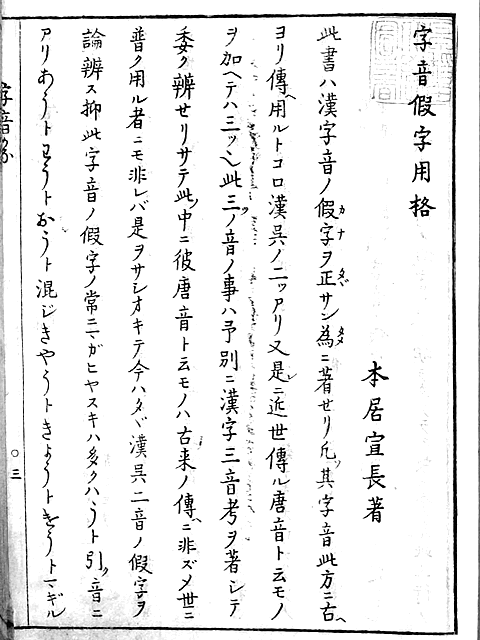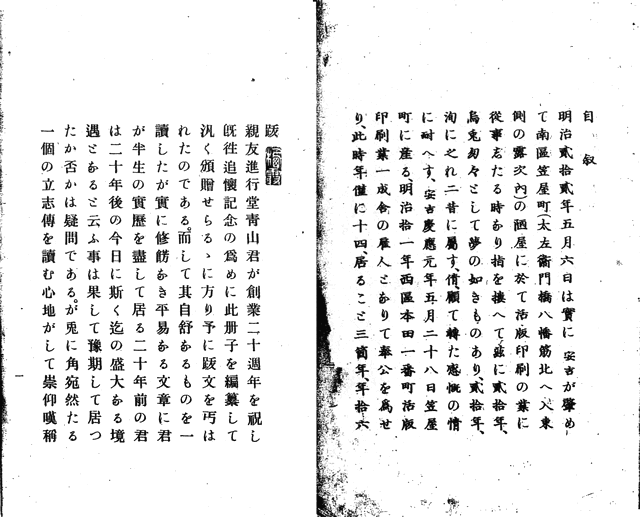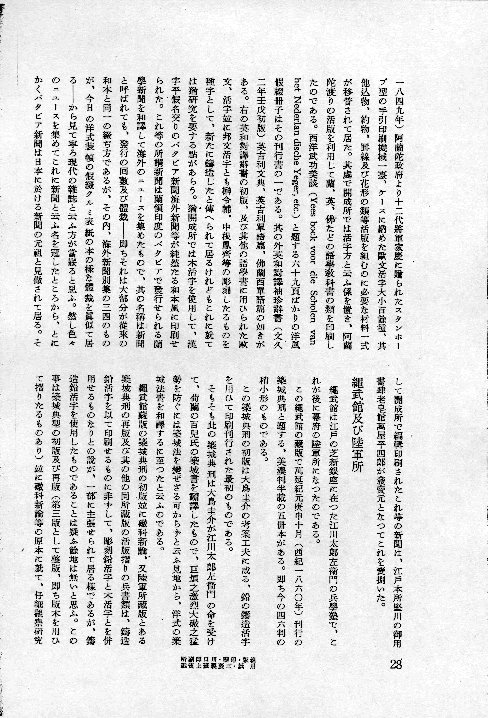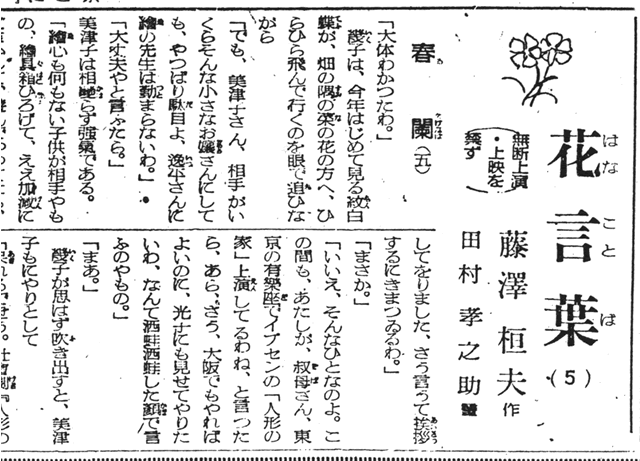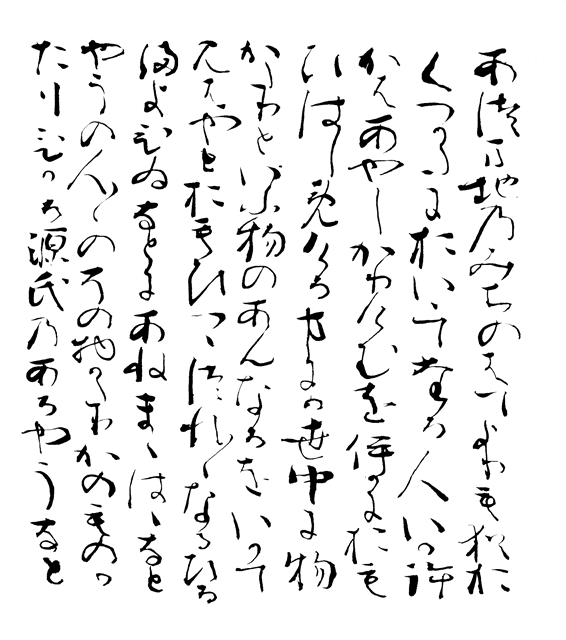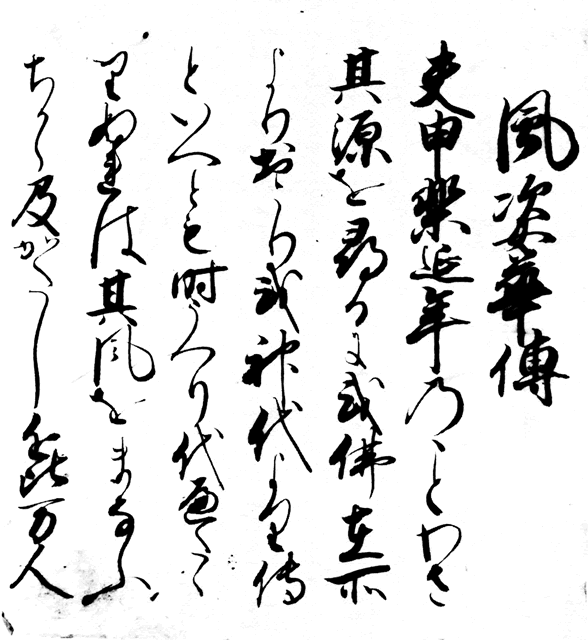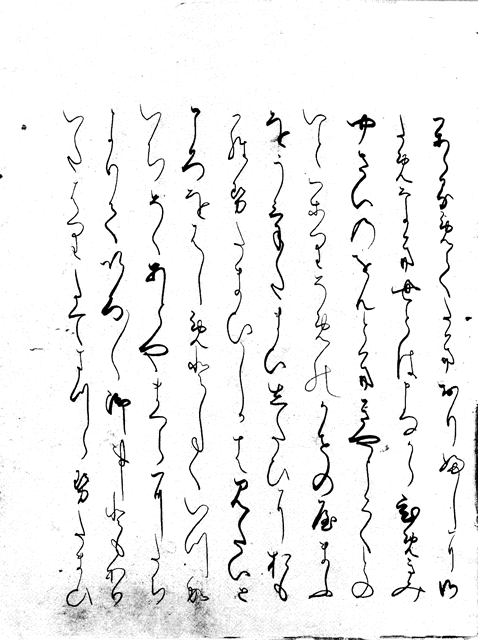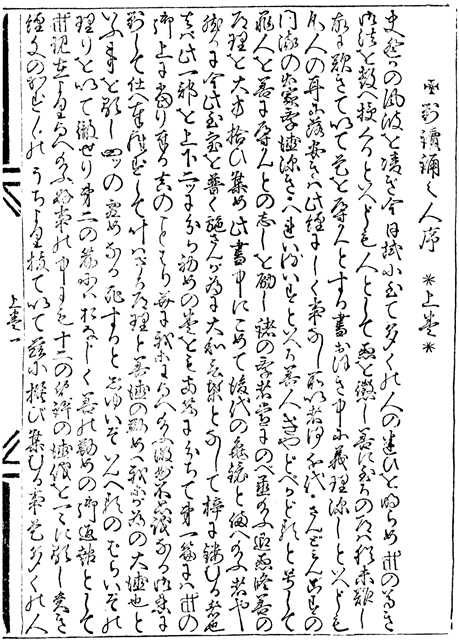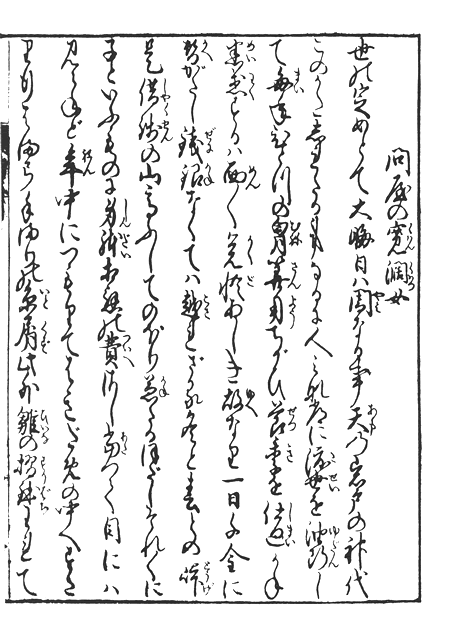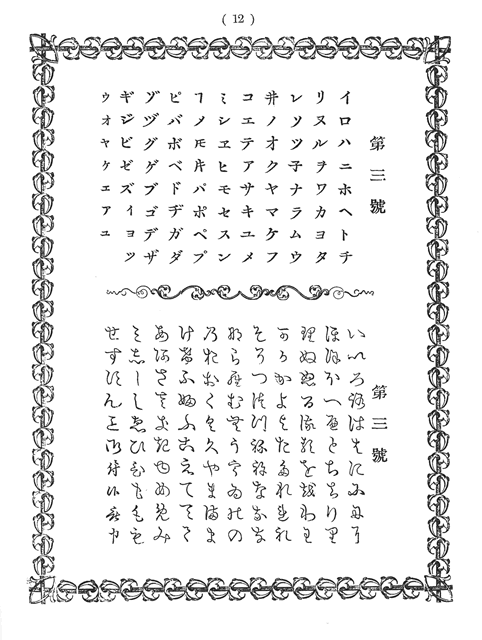
書体の基礎知識 和字書体編
黎明本様体──和字のヴェネチアン・ローマン体
和字(平仮名と片仮名)書体の歴史とは、おもに文芸書をしるした「和様漢字+平仮名」の系統と、おもに学術書をしるした「楷書漢字+片仮名」の系統があります。
前者は欧字書体のイタリック体もしくはスクリプト体に相当し、後者はローマン体に相当するものと考えられます。この「楷書漢字+片仮名」の系統において、片仮名とならんで平仮名が登場したとき、和字のローマン体が誕生したといえるでしょう。
それは江戸時代後期のことです。今回は、国学・蘭学の三冊の書物から、和字のヴェネチアン・ローマン体誕生のそのときにせまっていきたいと思います。
1 『字音假字用格(じおんかなづかい)』 1776 錢屋利兵衞
京都の錢屋利兵衞によって1776年(安永5)に刊行されました。序題は「字音迦那豆訶比」、版心書名は「字音かな」となっています。序は須賀直見が書いています。一冊のみで、27cmサイズの四つ目綴じ製本です。
著者の 本居宣長(1730―1801)は江戸中期の国学者です。伊勢の人で、号を舜庵(春庵)・鈴屋といいます。京都に出て医学を修める一方で、源氏物語などを研究しました。のちに賀茂真淵に入門しました。古道研究をこころざし、「古事記伝」の著述に30余年にわたって専心しました。
また、「てにをは」や用言の活用などの語学説、「もののあはれ」を中心とする文学論、上代の生活・精神を理想とする古道説など、多方面にわたって研究・著述に努めました。
著書に『初山踏(ういやまぶみ)』『石上私淑言(いそのかみささめごと)』『詞の玉緒』『源氏物語玉の小櫛(おぐし)』『古今集遠鏡』『玉勝間』『鈴屋集』などがあります。
2 『仮字本末』 1850  三書堂
国学とは江戸中期に興った文献学的方法による古事記・日本書紀・万葉集などの古典研究の学問で、儒教・仏教渡来以前の日本固有の文化を究明しようとしたものです。契沖(けいちゆう)を先駆とし、荷田春満(かだのあずままろ)・賀茂真淵・本居宣長・平田篤胤(ひらたあつたね)らによって確立しました。皇学(皇国の学の意)ともいいます。
文政年間に書かれた国学者・伴信友(1773―1846)の遺稿をその子信近が校訂し、1850年(嘉永3)3月に長沢伴雄(1806―59)の序を添えたうえで、江戸・大坂・京都の書肆から刊行されたのが『仮字本末』です。
刊本は上巻之上、上巻之下、下巻、付録の合計4冊からなっており、朝鮮綴で薄紺色無地の表紙がつけられています。「楷書漢字+平仮名」が登場した初期の印刷物だと思われます。
3 『歩兵制律』 1865  陸軍所
洋学とは西洋の学問のことです。とくに蘭学とは江戸中期以降、オランダ語によって西洋の学術・文化を研究した学問です。享保年間(1716―1736)、青木昆陽・野呂元丈(のろげんじよう)の蘭書の訳読に始まり、前野良沢(まえのりようたく)・杉田玄白・大槻玄沢(おおつきげんたく)ら多数の蘭学者が輩出、医学・天文学・暦学・兵学・物理学・化学など自然科学全般にわたりました。
大鳥圭介(1833―1911)は、縄武館につとめていたとき、『築城典刑』『砲科新論』を翻訳して、独自の活字をもちいて出版することに着手しました。大鳥は西洋の活字が便利だということを知って、独力で蘭書にもとづいていろいろ研究したそうです。
『歩兵制律』(陸軍所 1865 印刷博物館所蔵)は、オランダの書物を開成所の教員であった川本清一が翻訳し、大鳥の金属活字をもちいて印刷したものです。『歩兵制律』は「楷書漢字+平仮名」で組まれています。
●字音假字用格(じおんかなづかい)
●仮字本末
●歩兵制律
明治本様体──和字のオールド・ローマン体(前編)
長崎製鉄所主任だった本木昌造は、ウィリアム・ガンブルを活版伝習所の技師長として招聘しました。ここでは活字鋳造法と活字版印刷術全般にわたる技術を伝授しました。これがわが国の活字版印刷術の基礎となったのです。
まもなく長崎製鉄所付属活版伝習所は解散し、その源流は二派に分かれました。ひとつは本木昌造の流れを汲む門人達によって全国に覇をとなえた一派で、その代表が東京築地活版鋳造所です。他のひとつは製鉄所にとどまって活字製作に従事した人達で、のちに工部省勧工寮活版所となり、幾多の変遷をへて官業活版の源流を受け継いだのが内閣印刷局(現在の国立印刷局)です。これらとは別に神崎正誼による活版製造所弘道軒では、独自の活字書体をあらたに制作しました。
これらの和字書体に共通するのは、黎明期本様体(和字のヴェネチアン・ローマン体)がもっていた彫刻風の荒々しさが少なくなり、丸みを帯びた動きのなる書風にと変化しているということです。これを明治本様体(和字のオールド・ローマン体)としたいと思います。
1 『二人比丘尼色懺悔』 1889  活版製造所弘道軒
神崎正誼(1837―91)は1874年(明治7)に「活版製造所弘道軒」を創立しました。そして新しい活字書体の版下の揮毫を、書家の小室樵山(正春 1842―93)に依頼しました。
尾崎紅葉の『二人比丘尼色懺悔』(吉岡書籍店 1889)にも、本文に四号相当の弘道軒清朝体が用いられています。新著百種の第一作として刊行されたもので、印刷は国文社です。『二人比丘尼色懺悔』は、奇遇の巻・戦場の巻・怨言の巻・自害の巻からなっています。
2 『長崎地名考』 1893  東京築地活版製造所
株式会社東京築地活版製造所の初代社長・平野富二は、1889年(明治22)に社長を辞任しました。本木昌造の長男・本木小太郎が社長心得になりますが、本木小太郎は病弱だったので、曲田成が3代目社長に就任しています。
香月薫平著『長崎地名考』は、上巻・下巻・附録の3冊からなっています。1893年(明治26)11月に長崎の虎與號商店から発行されています。奥付には、印刷所は東京築地活版製造所、印刷人は曲田成(1846―94)とあります。
3 『内閣印刷局七十年史』 1943  内閣印刷局
印書局は明治5年9月に創設されて、はじめは太政官正院の中におかれていました。明治7年に工部省製作寮所管の活版所(勧工寮が明治6年11月に廃止されて製作寮の所管に移る)を移管併合して、明治8年に大蔵省紙幣寮に属することになります。
1877年(明治10)年4月、大蔵省紙幣局となったときに、紙幣局活版部で『活版見本』が発行されています。ここにみられる平仮名、とりわけ5号平仮名が『内閣印刷局七十年史』の本文で用いられた書体の源流だと思われます。
『内閣印刷局七十年史』の本文に用いられた和字書体は、印刷局の伝統的な書風であり、明治前期の典型的な書風といってもいいのではないでしょうか。
●二人比丘尼色懺悔
●長崎地名考
●内閣印刷局七十年史
明治本様体──和字のオールド・ローマン体(後編)
東京築地活版製造所と並び称せられるのが秀英舎鋳造部製文堂です。1882年(明治 15)東京築地活版製造所から小倉吉蔵を招いて製文堂を創設して、活字の製造販売に進出したのがはじまりです。秀英舎は、1935(昭和10)に日清印刷と合併して大日本印刷となりました。
青山進行堂活版製造所は東京築地活版製造所系統の活字書体を継承していたと思われます。江川活版製造所と特約して活字製造に着手し、都村活版製造所、岡島活版所の活字書体を継承しましたが、1916年(大正5)には「篆書ゴシック」を開発して業界の注目を集めました。国光社は吉田晩稼が版下を書いたといわれる独自の活字書体を開発しています。
これらの和字書体もまた、丸みを帯びた動きのある明治本様体(和字のオールド・ローマン体)ですが、昭和本様体(和字のトランジショナル・ローマン体)の萌芽もみられます。
1 『尋常小學國語讀本 修正四版』 1901  国光社
西澤之助(1848―1929)は1888年(明治21)に国光社を創立しました。国光社は伝統的な女子教育の雑誌 『女鑑』 などで一定の地歩を占めました。
1900年(明治33)に西澤之助は国光社社長を辞し、日本女学校を設立しています。また国光社は多くの教科書を発行している大手教科書会社でもありました。
国光社活字とは国光社が独自に開発したとされる書体で、吉田晩稼(香竹1830―1907)が版下を書いたといわれています。
2 『少年工芸文庫第八編 活版の部』 1902  秀英舎
『少年工芸文庫』は全12冊発行されています。著者の石井研堂(民司1865―1943)は、民衆の立場から明治以来の日本の近代化を探求・記録した博物学者です。
発売元の博文館は、明治時代には日本の出版界をリードしていましたが、大正から昭和にかけて雑誌を中心に発展してきた講談社などに押され、終戦後に解散してしまいました。大日本印刷の前身の秀英舎で印刷されていますので、本文はいわゆる秀英舎前期四号です。
3 『富多無可思』 1909  青山進行堂活版製造所
青山安吉(1865―1926)は1909年(明治42)5月、青山進行堂活版製造所の創業20年を記念して『富多無可思』を発行します。この約300ページにもおよぶ線装(袋とじ)の記念誌は、活字の見本帳であり、印刷機械などの営業目録でもあります。
『富多無可思』の青山安吉による「自叙」は四号楷書体活字、竹村塘舟による「跋」は四号明朝体活字で組まれていますが、和字書体は共通のものです。
●尋常小學國語讀本 修正四版
●少年工芸文庫第八編 活版の部
●富多無可思
昭和本様体──和字のトランジショナル・ローマン体
昭和前期の活字書体の制作は、大きくふたつにわけられます。ひとつは活字鋳造会社系で、一般販売もしくは自社の印刷機械用として制作しました。もうひとつは印刷会社・出版社系で、自社の印刷物・出版物専用として制作しました。
そのなかで三省堂、精興社のような「印刷会社・出版社系」は、とりわけ明朝体と組みあわせることを目的とした本文用和字書体で独自性を出すように、しのぎを削ってきたようです。
太平洋戦争後の1946年(昭和21)から1950年(昭和25)までの約四年間、北海道では札幌市を中心として出版ブームがおこりました。このときに北海道各地で刊行された文芸書や教養書を「札幌版」といいます。
『広辞苑』以前に新村出の編著で『辞苑』という国語辞典が1935年(昭和10)に発刊されていました。この『辞苑』は博文館から出版され、大ベストセラーとなっていました。
『辞苑』には、見出し語にアンチック体の和字書体がもちいられていました。もちろん『広辞苑』初版の見出し語もアンチック体の和字書体でした。ところが『広辞苑』第五版の見出しは太明朝体用としてつくられていた和字書体のようです。初版でも第五版もアンチック体の説明で「本辞典の項目に用いた見出しのかな文字」がアンチック体である、としたために混乱が生じています。
そこで筆者は、アンチック体と太明朝体用和字書体とは異なる書体とみたいと思います。たとえば「の」の頂点がほぼ同じ太さになっているのがアンチック体、細くなっているのが太明朝体用和字書体ということができます。
新村出(1876―1967)は京大教授で、ヨーロッパ言語理論の導入に努め、日本の言語学・国語学の確立に尽力しました。とくに国語史や語原・語誌・語釈に関する研究、外来語や南蛮文化に関する考証などの多方面にわたる業績をあげました。
●辞苑